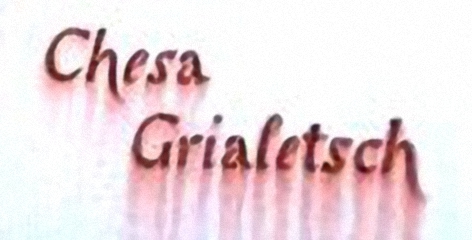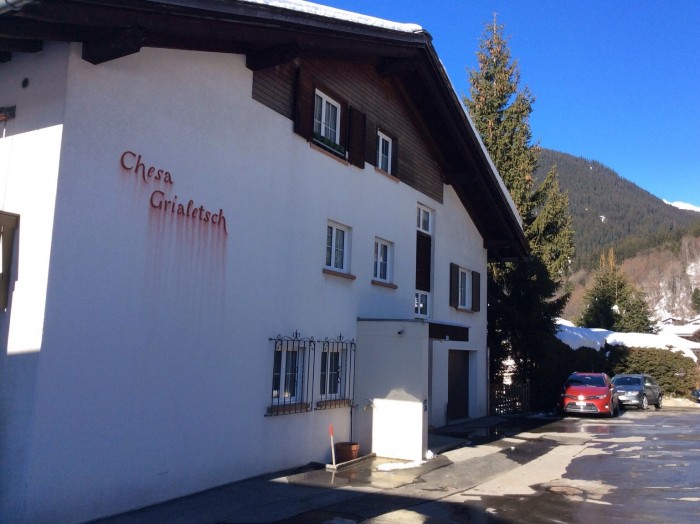
Hausbeschriftung
Der Maler möchte die Hauswand neu malen und bräuchte dazu eine Schablone mit der Schrift.
Leider habe ich keine Ahnung und kann diese somit nicht erstellen.
Habt ihr vlt. eine Idee welche Schrift das sein könnte?
Guten Morgen, Jonick, möglicherweise ist das eine frei gezeichnete Schrift. Soll es denn genau dieselbe wieder sein? Wenn es eine gezeichnete Schrift ist, könnte man sie nach einem Photo, das nicht so stark perspektivisch verzerrt ist, am Rechner nachvectorisieren und von dem Vector dann eine Schablone schneiden lassen. Wenn es eine Satzschrift ist, wäre zur Identifikation auch ein weniger verzerrtes Bild hilfreich, wo man vielleicht weniger von der schönen schweizer Landschaft, aber mehr von der Schrift sieht.
Netter Drop-Shadow-Effekt, übrigens. ;-)
Das nach links kippende a und das ausgestellte h erinnert etwas an die Windsor:
Vom Duktus und den anderen Zeichen passt die natürlich so gar nicht und das wird garantiert irgendwie handgeschrieben sein.
Auch wenn in dem Schriftzug einiges nicht zusammen passen mag, fände ich es schade, wenn man sowas mit einer Satzschrift per Schablone an die Wand bringt.
Das habe ich leider fast vermutet.
Werde es dem Maler überlassen. Eine vektorisierung wird ihm aber wahrscheinlich zu teuer sein. Somit wird es wohl eine alternativ Schrift werden.
Schön gesagt. Die »e« des alten Schriftzuges scheinen übrigens aus einer anderen, kursiven, Schrift zu stammen als der Rest. Jonick, wäre Dir denn mit Schriftempfehlungen für den neuen Schriftzug geholfen?
Werde es dem Maler überlassen.
Nichts gegen Maler, aber das ist schon etwas leichtsinnig. Typographie oder Kalligraphie gehören in der Regel einfach nicht zu ihrem Berufsbild. Dann ist es schon besser, wie von Kathrin vorgeschlagen hier ein paar Empfehlungen einzuholen und dann dem Maler verbindliche Vorgaben zu machen. Man kann den Gesamteindruck eines schönen Hauses durch eine verhunzte Schrift empfindlich beeinträchtigen.
Ich bin Gestalter Werbetechniker von Beruf und wirklich kein Ass was Schriften anbelangt. Falls ihr also Schriftideen habt, welche auf eine solche Hausmauer passt, bin ich sehr glücklich über eure Hilfe. Vielen Dank!
Ich bin Gestalter Werbetechniker von Beruf …
Heißt das, Du kannst dem Maler eine Schablone plotten, wenn Du eine passende Schrift gefunden hast?
Ganz genau. Das ist mein Job.
Also wenn Du eine konservative, vorsichtige Lösung willst, die gefällig ist und niemandem wehtut, dann nimm eine kursive Garamond, möglicherweise mit Swash-Formen, das erinnert ein wenig an die alte Lösung, wirkt immer professionell und sauber und niemand wird sich beschweren. Aber es gibt sicher interessantere Ansätze als diesen und wenn man es ordentlich machen will, muß man sich auch mit dem Stil des Hauses beschäftigen.
Je nachdem, wieviel freie Hand Du gegenüber dem Eigentümer hast, würde ich aber unbedingt auch die Proportionierung zur Façade neu überdenken. Das ist mindestens so wichtig wie der eigentliche Schriftzug. Die derzeitige ist nach meinem Geschmack ein bißchen zu klein. Ein Drittel größer würde besser passen, bei der Gelegenheit würde ich die Schriftlinie der unteren Zeile (falls das wieder so zweizeilig wird) möglicherweise auf eine Höhe mit den Fensterbrettern bringen. Das müßte man aber einfach mal anhand eines unverzerrten Façadenbildes am Rechner schieben. Derzeit scheint mir die Schrift etwas zufällig proportioniert und positioniert zu sein (ich will nicht sagen: hingerotzt), aber jedenfalls nicht optimal in das Gesamtbild der Façade integriert.
Eine Garamond an einem Bauernhaus in den Alpen? Oder in welchen Bergen es auch steht. Wehtun würde mir das nicht, aber es würde mich vielleicht erheitern und zu hämischen Bemerkungen hinreißen. Konservativ wäre das in meinen Augen nicht, nur verfehlt.
Mit konservativ meinte ich hier: Einerseits an die alte Gestaltung angelehnt, andererseits besser als vorher. Natürlich wäre es besser, einen Schnitt zu machen und die alte Beschriftung komplett außen vor zu lassen. Ich weiß aber nicht, was der Kunde von Jonick vorgegeben hat. Wenn ich mir den Anfang des Stranges ansehe, vermute ich eher, daß ein kompletter Neuanfang nicht gewünscht ist. Deshalb mein Einstieg mit der kursiven Garamond, den ich ja auch gebührend relativiert hatte.
Tut mir leid, aber diese Chancery-Schriften sehen mir immer ein bißchen bemüht aus. Halte ich nicht für die bessere Lösung gegenüber einer kursiven Antiqua. :-?
Das geht mir auch so. Wobei ich Martins Ansatz der inhaltlichen/geografischen Herleitung ja sehr schön finde – da wird es doch sicherlich auch noch andere schöne Schriften geben?
Wenn ich eine Aufgabe bekäme, eine passende Schrift für dieses Haus zu suchen, würde ich mich mit den Engadinerhäusern befassen. Deren Dekor ist italienisch beeinflußt, habe ich auf die Schnelle gefunden, mit den sogenannten Sgrafitti, einer Putz- und Kratztechnik. Da diese Häuser über sehr lange Zeit gebaut wurden, wird sich auch das Dekor verändert haben. Wie hat man diese Häuser um 1800 beschriftet? Ich weiß es nicht, aber ich würde die französischen Schriften sicherlich links liegenlassen. Eine echte Cancellaresca (etwa die von Amphiareo, Tagliente, Cresci oder Arrighi, auch Manutius und Palatino) sieht natürlich anders aus als diese modernisierten Formen, die sicherlich allein dadurch gewönnen, wenn sie nicht nach digitalen Schriften kopiert, sondern von Hand mit dem Flachpinsel gezeichnet würden. Wie Schnitzel es schon sagte: mit einer Satzschrift kommt man sicherlich kaum zu einem rundum befriedigenden Ergebnis. Wenn es aber schon eine Billiglösung ohne Aufwand sein soll, dann wäre eine schöne Cancellaresca oder vielleicht eine italienische Renaissance-Kursive (Griffo und Mardersteig) zu bedenken. Vielleicht auch die Delphin von Georg Trump. Nur kann man eine Satzschrift nicht ohne erheblichen Wirkungsverlust auf die Größe einer Wandbeschriftung bringen. Vielleicht noch mit einem der feinen Display-Schnitte der kursiven Arno, da geht man immerhin auch noch auf dem italienischen Pfad und bringt keine so starke Klobigkeit auf die Wand.
Hast du dafür ein Link oder eine genaue Bezeichnung? Danke :)
Dieses könnte funktionieren. Habe aber noch nicht damit gearbeitet, kann daher nichts genaues sagen. Lt. Beschreibung paßt es aber.